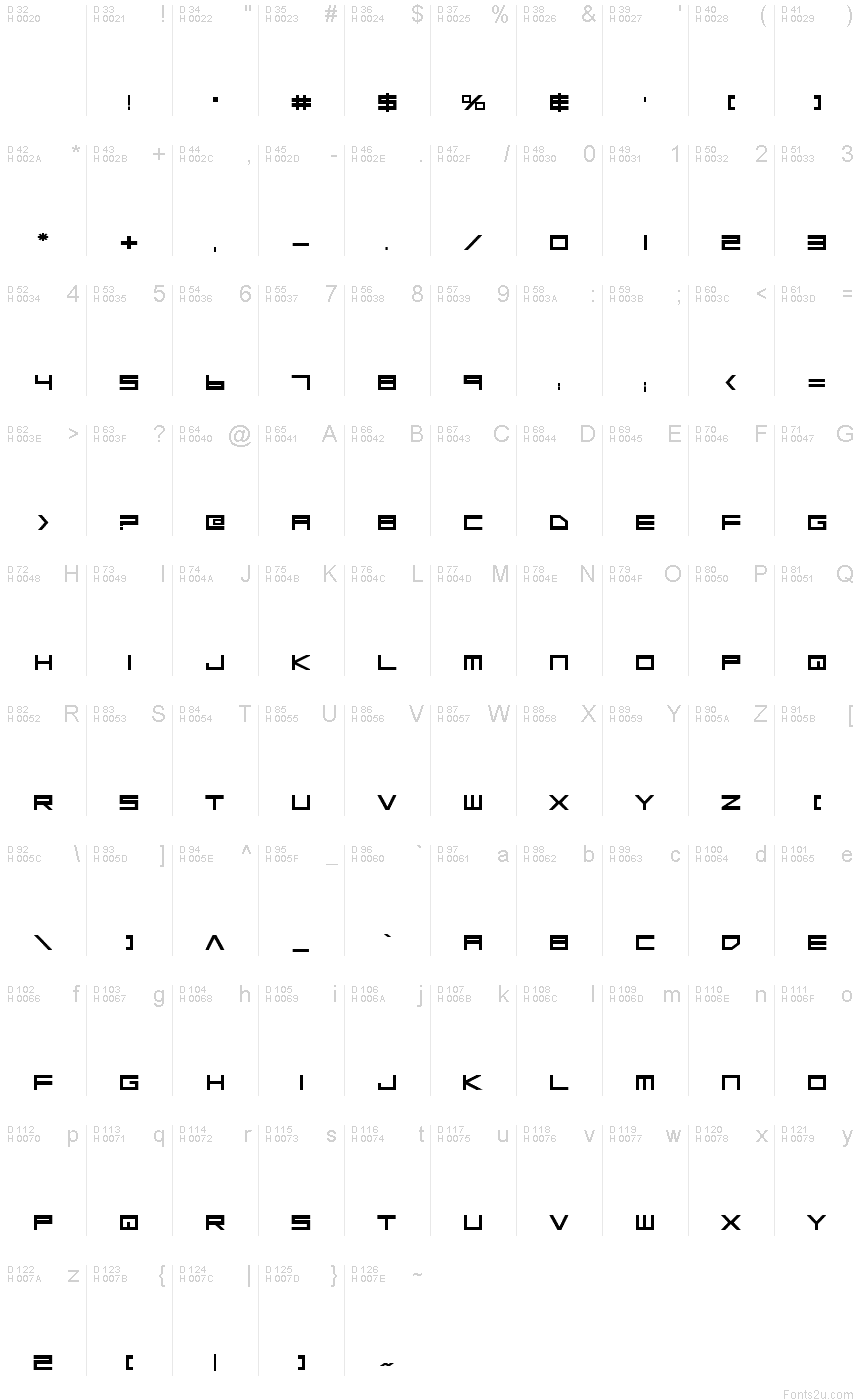
Low Gun Screen Bold Expanded è un font display techno, gratuito ed esteso, creato da Iconian Fonts. È costruito su forme rettangolari massicce che sembrano provenire direttamente da un pannello di controllo sci-fi. Le lettere sono larghe, squadrate e suddivise in segmenti che ricordano uno schermo, conferendo al carattere un ritmo digitale deciso con un tocco leggermente industriale.
Si adatta perfettamente a loghi di giochi, titoli di poster, copertine di album, grafiche per lo streaming e branding in stile interfaccia utente, dove quell'estetica elettronica e squadrata colpisce subito nel segno. Essendo un font gratuito, è particolarmente indicato per titoli brevi, schermate di apertura e wordmark, poiché le lettere larghe e gli spazi vuoti rendono anche una riga breve un elemento dal design tecnico e curato, non banale.